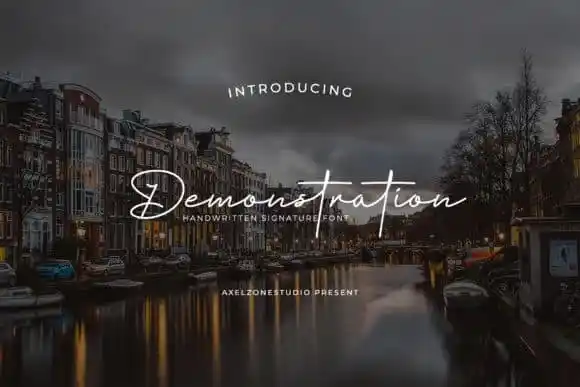
Demonstration Handwritten Font – Fonte Grátis
Demonstration Handwritten Font
A Demonstration Handwritten Font é uma tipografia digital para assinatura que Axelzonestudio criou com caracteres dançando ao longo do nível da base de linhas. Esta fonte vem diretamente de um mundo onde a arte da escrita ficcionada toca níveis íntimos e românticos, tornando-a perfeita para criar designs em festivais de casamento, cartões de agradecimento, mensagens pessoais, cartazes de aniversário, logotipos ou até mesmo cartões de visita. Suas formas fluidas e seus traços delicados criam um efeito que é quase como se a própria escrita estivesse vivendo e respirando na página, tornando-a uma escolha ótima para qualquer design que precise de uma pequena dose de autenticidade humana. Este tipo gráfico romântico e suave é perfeito para aqueles que buscam um toque de personalização em seus projetos gráficos, seja no meio da confeitaria digital, na comunicação social ou em qualquer outro esforço de design.